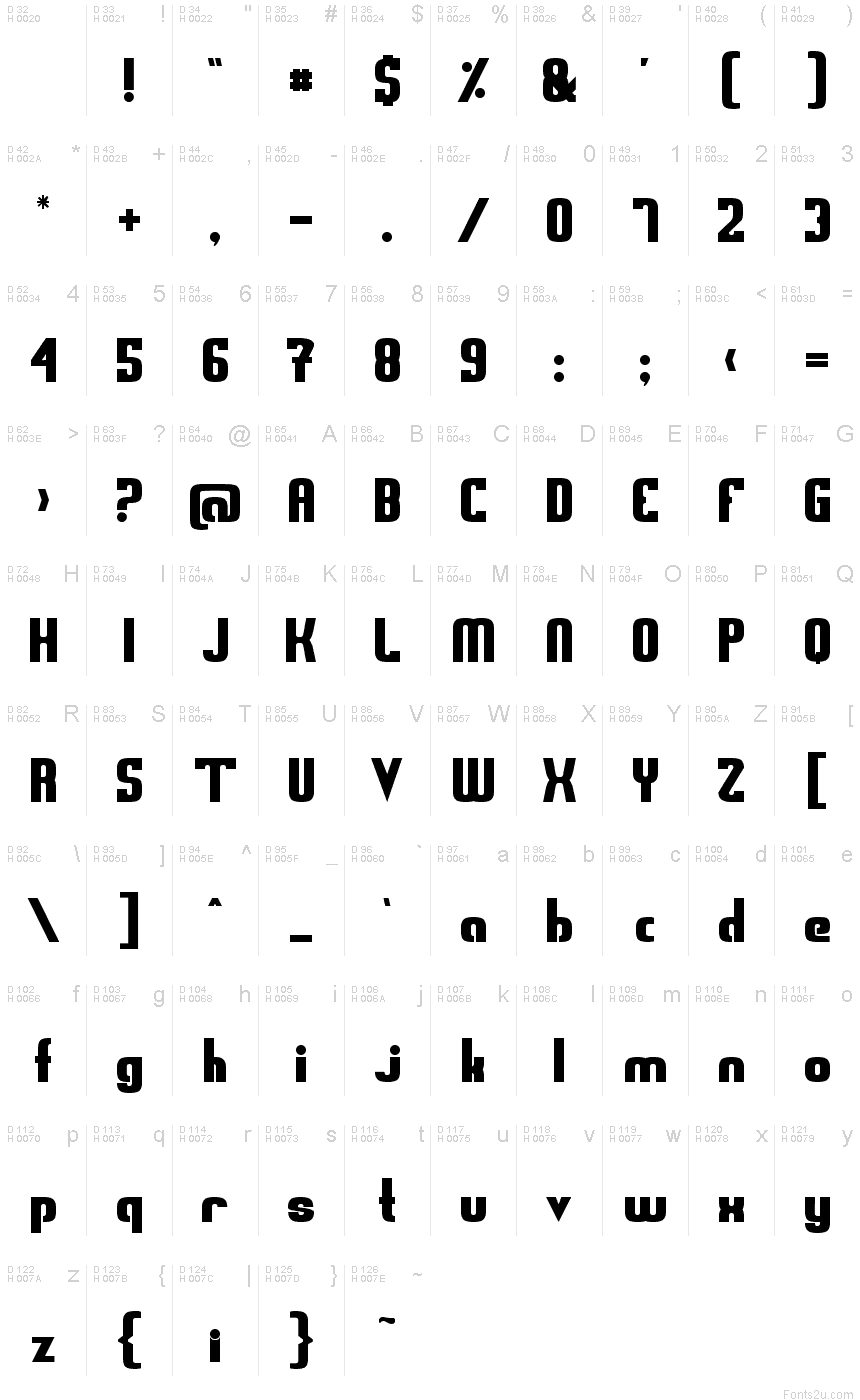
Sweden Funkis Straight
Sweden Funkis Straight autorstwa Samuela Parka to nowoczesny, darmowy font displayowy z wyraźnym, skandynawskim funkowym klimatem. Litery są przysadziste, ciężkie i miękko zaokrąglone. Blokowa masa łączy się tu z zabawnymi, wyciętymi narożnikami i ciasnymi wewnętrznymi zawijasami, co nadaje słowom skoczny, retro rytm.
Świetnie sprawdzi się na plakatach, okładkach płyt, w brandingu kawiarni, grafikach festiwalowych czy krótkich nagłówkach, gdzie ten wesoły klimat lat 70. może w pełni wybrzmieć. Jako darmowy krój jest idealny również do plansz tytułowych i szkiców logo, zwłaszcza gdy szukasz kompaktowych, „mięsistych” liter, które wydają się przyjazne, a nie zbyt wymuskane.